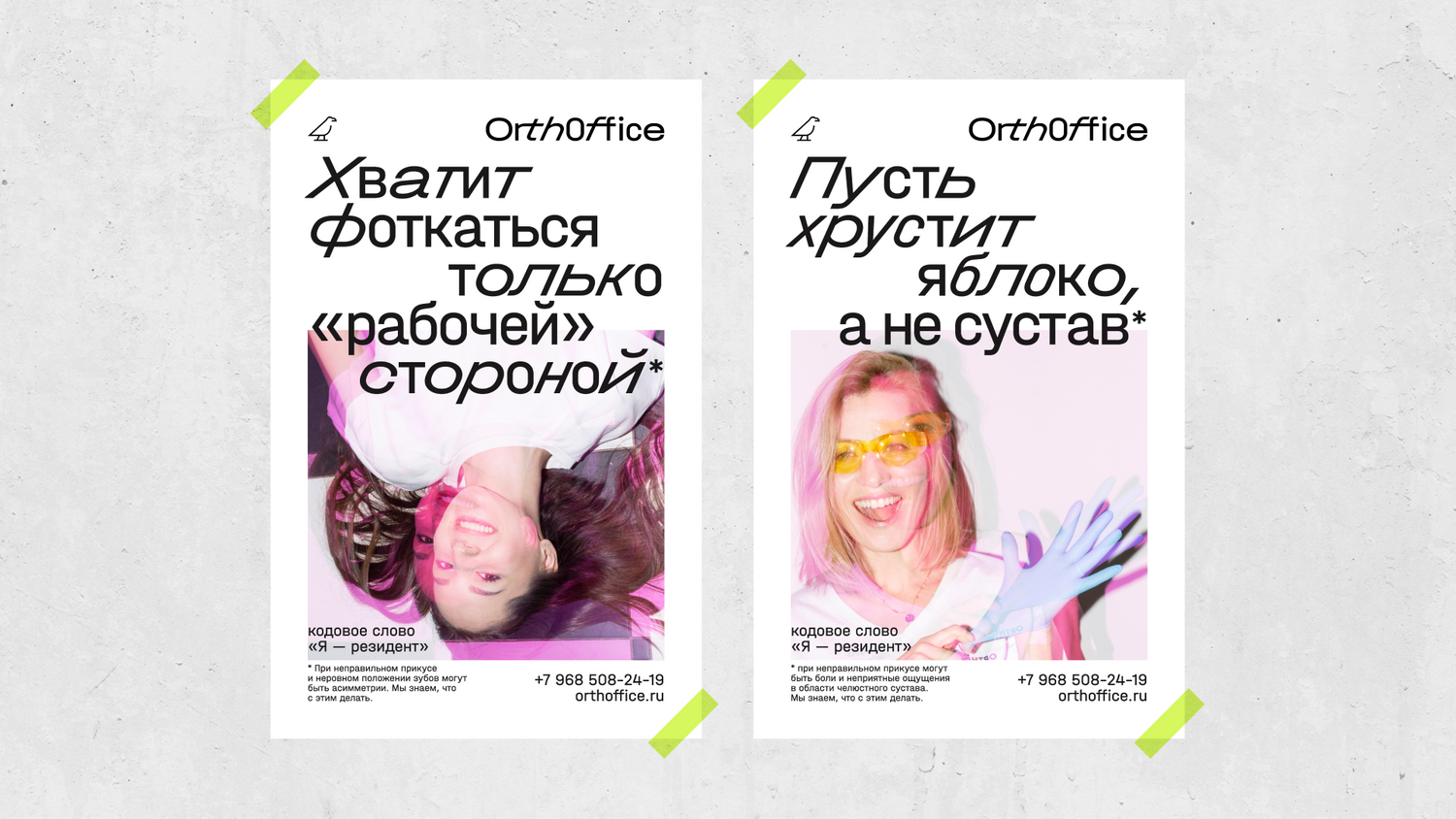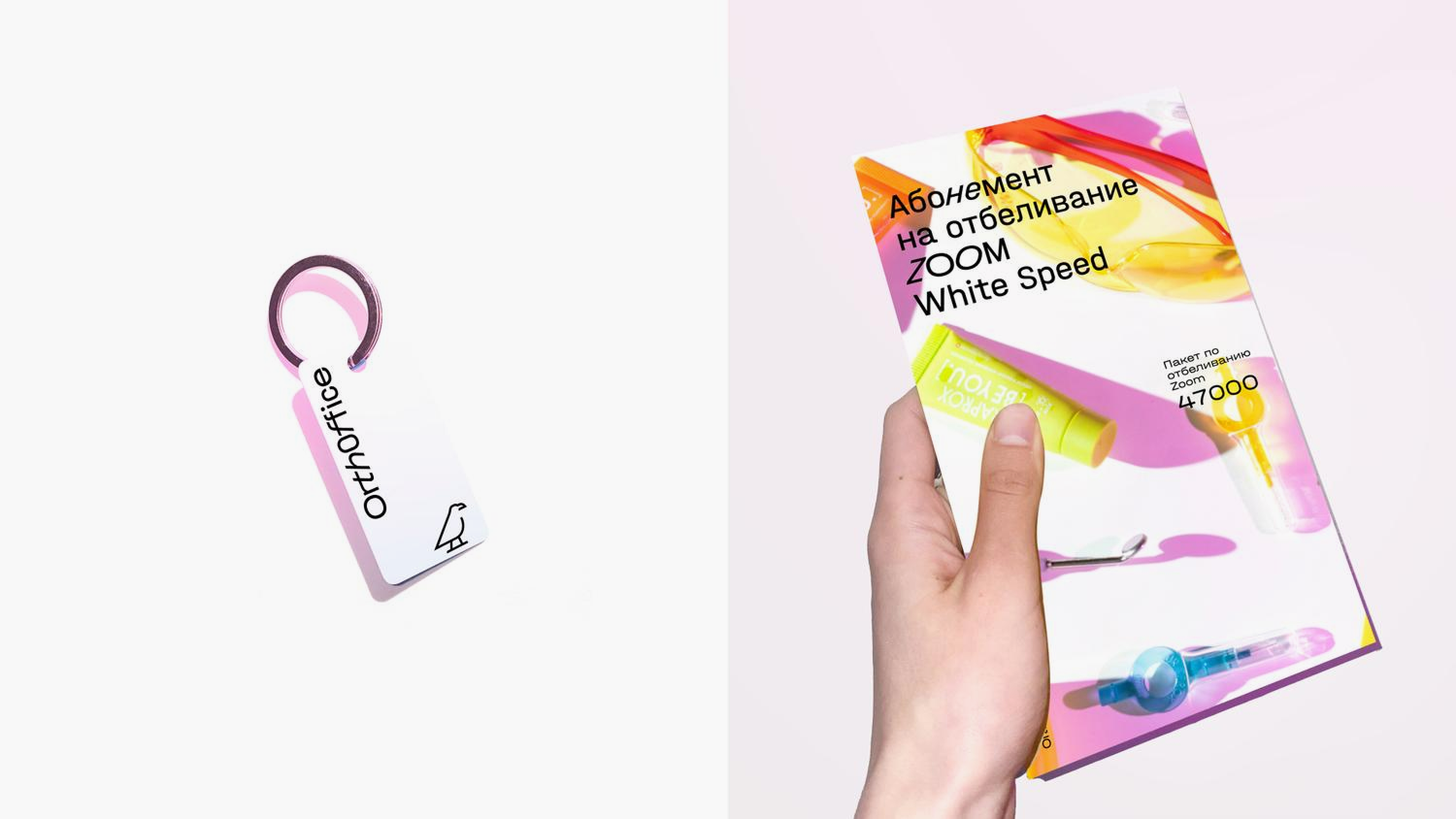
Halvar в работе: Ортофис
Halvar Breit, Mittel и SuperSlanted изображают исправление прикуса
Ортофис — стоматологическая клиника, в которой можно, например, исправить прикус или заказать сложный ортодонтический аппарат. За типографику в айдентике клиники отвечают несколько шрифтов из коллекции Halvar. Айдентику разработали в студии Holystick.
Halvar студии TypeMates — гротеск с грубым инженерным шармом и широким стилистическим спектром. 81 начертание Halvar — это три семейства: широкое Breitschrift, стандартное Mittelschrift и узкое Engschrift.